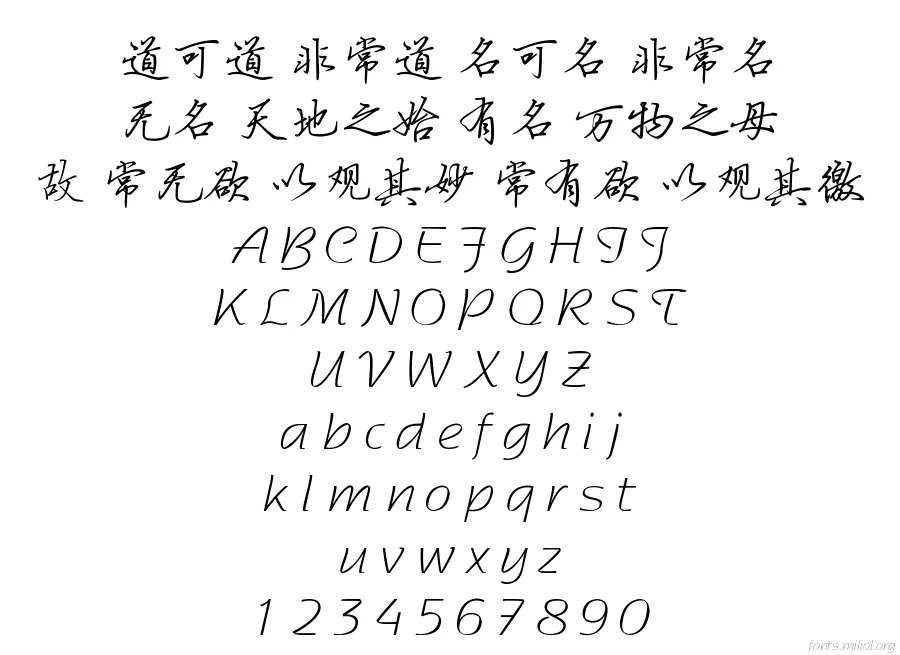
## 方正硬笔行书简体:传统书法与现代设计的完美融合
方正硬笔行书简体(FZYingBiXingShu-S16S)是一款兼具传统书法韵味与现代设计美感的优秀字体。这款字体以硬笔书法为基础,保留了行书特有的流畅线条与灵动笔势,同时通过标准化设计使其更符合现代印刷和数字显示的需求。其编号FZYBXSJW--GB1-0表明这是方正字库中经过专业设计的标准字符集产品。
该字体最显著的特点是笔画干净利落,转折处刚劲有力,整体呈现出一种挺拔俊秀的视觉效果。每个字符的间架结构经过精心调整,既保持了传统书法的艺术性,又确保了在各类媒介上的清晰可读性。特别适合用于需要展现文化底蕴的设计场景,如书籍装帧、品牌标识、广告宣传等。
作为方正字库的重要成员,这款字体严格遵循国家标准字符集规范,确保了在各类操作系统和应用软件中的兼容性。其独特的艺术表现力与实用功能的完美结合,使其成为设计师和文字工作者值得收藏的字体资源。